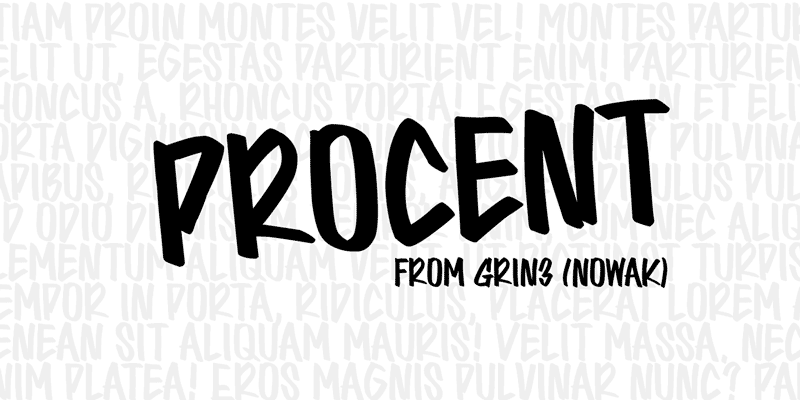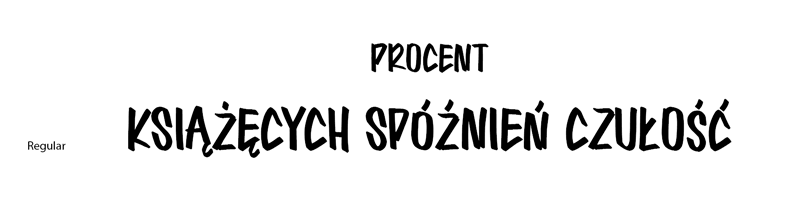
Font Procent
Zakupiliśmy font Procent polskiego projektanta Bartka Nowaka. Litery przypominają namalowane grubym pędzlem i nadają się doskonale jako fonty uzupełniające przy projektach reklam wykonywanych przez nasze studio.